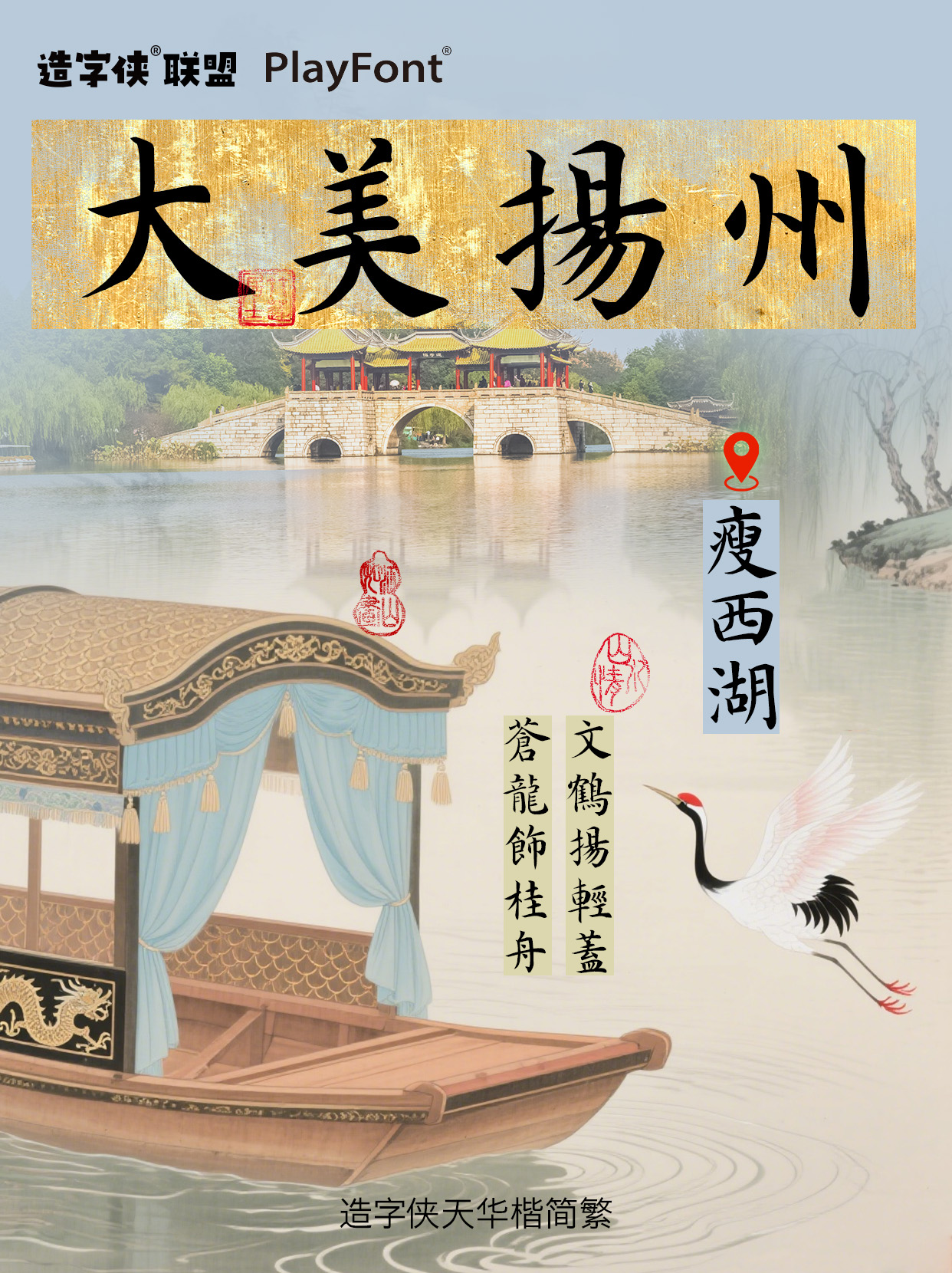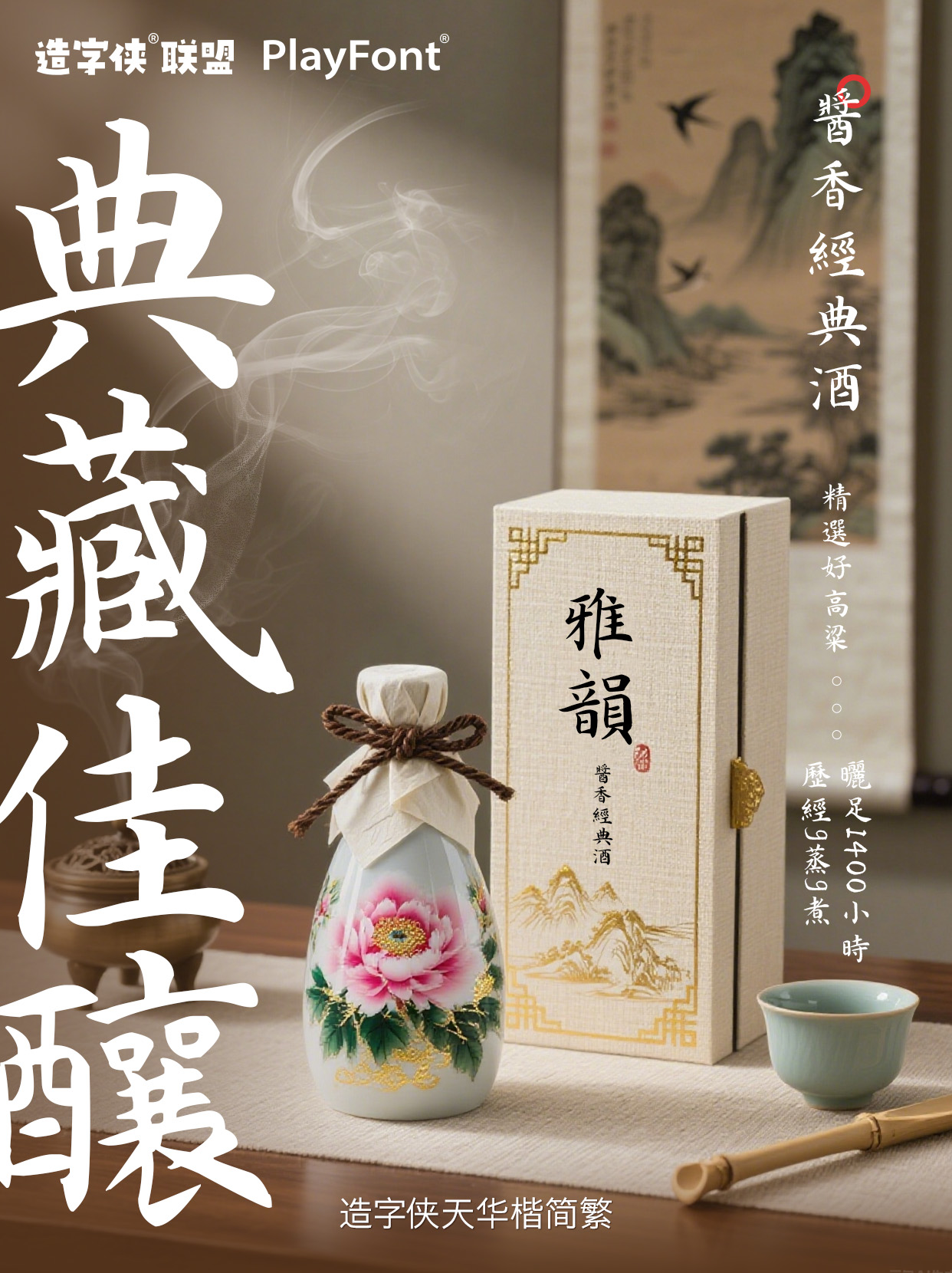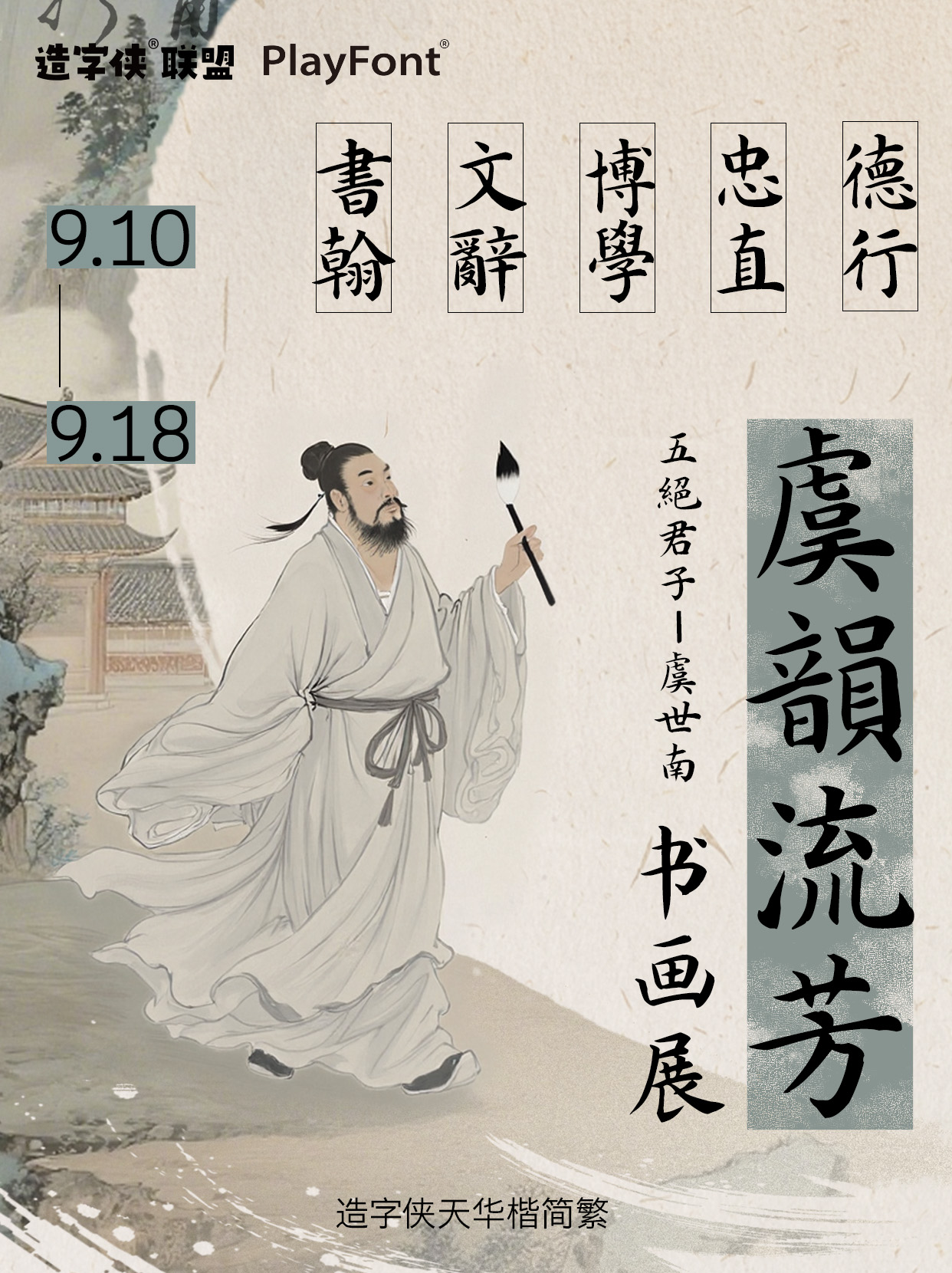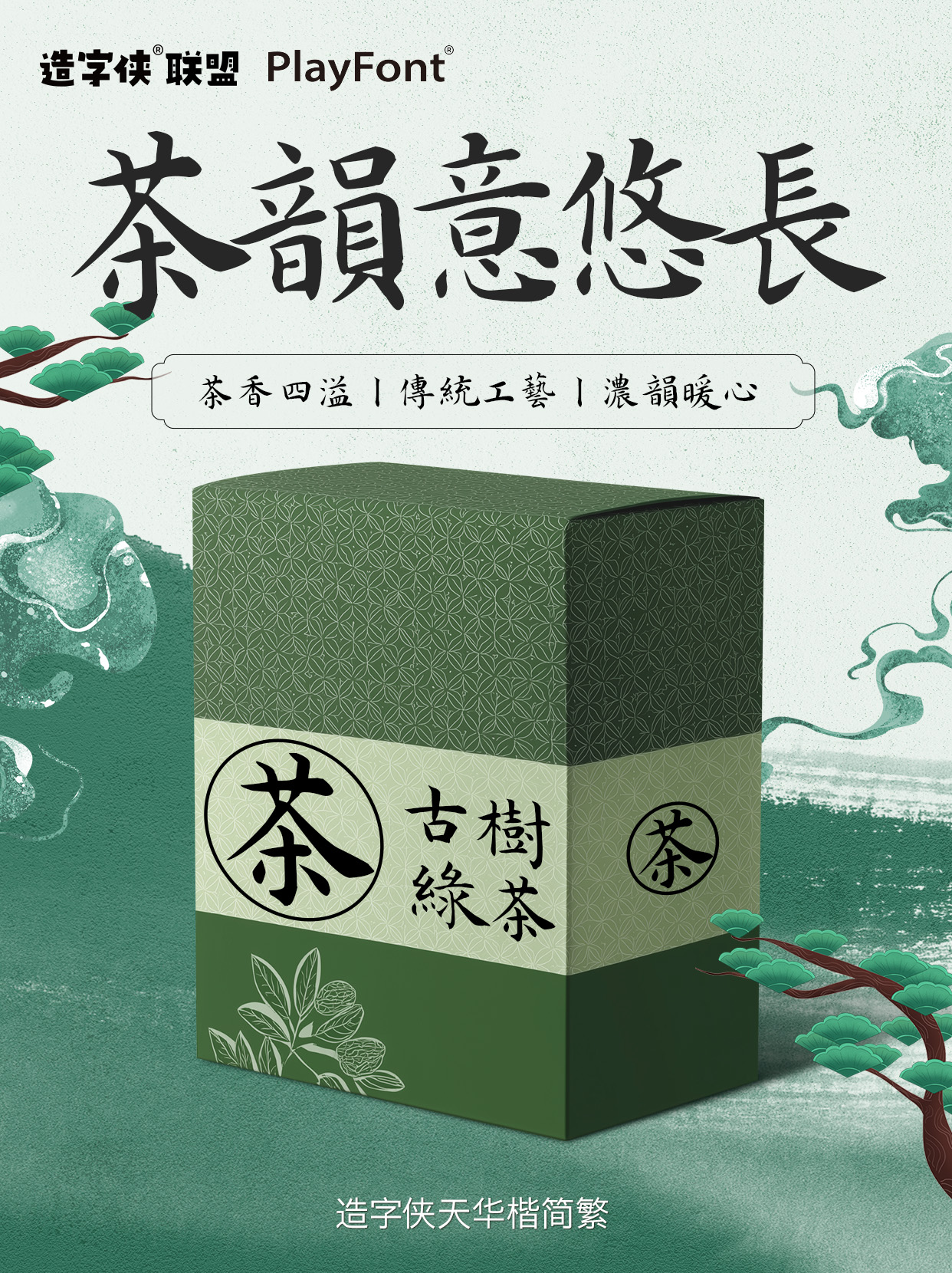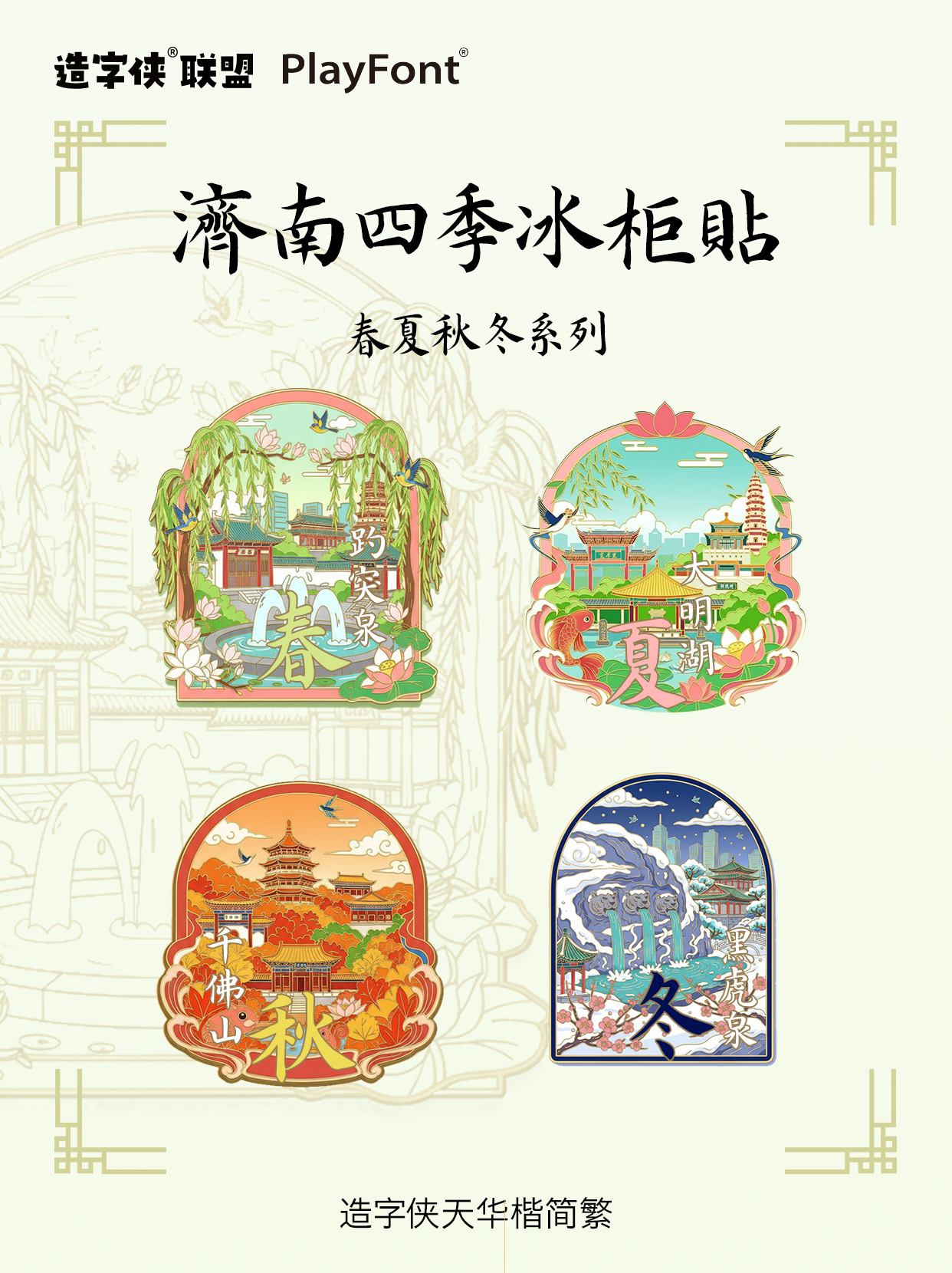
造字侠天华楷简繁
PlayFont-TianhuaGBT
圆润秀逸,外柔内刚
虞世南为初唐书法家,与欧阳询等并称 “初唐四大家”。其书法师法王羲之,楷书圆润秀逸、外柔内刚,《孔子庙堂碑》为代表作,对后世楷书发展影响深远。
造字侠天华楷取法虞世南楷书精髓,尽显“清秀”风骨。整体笔法秀丽圆润,结体端庄舒雅,兼具含蓄之美与骨力,形成 “虞体” 特色。适用于文化宣传、海报设计、包装、Logo、周边文创等多种应用场景。
运笔沉稳有力且不露锋芒,结体布局匀称且识别性极高,尽显儒雅、清秀,书卷气十足。
横画舒展,竖画劲挺,撇捺收放得当,进而撑起整字重心,尽显舒雅与从容。